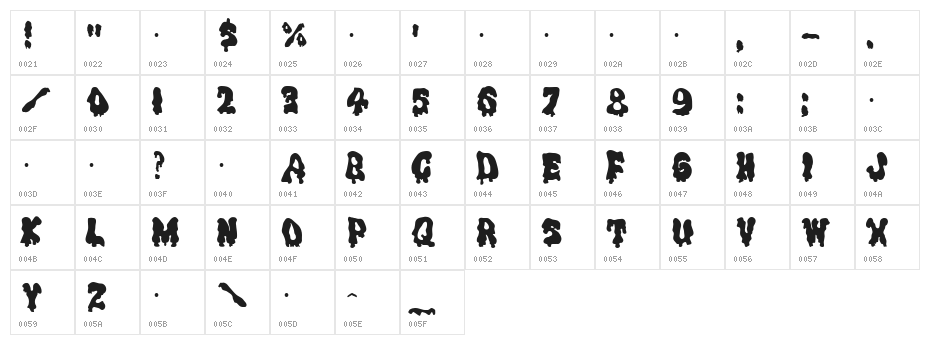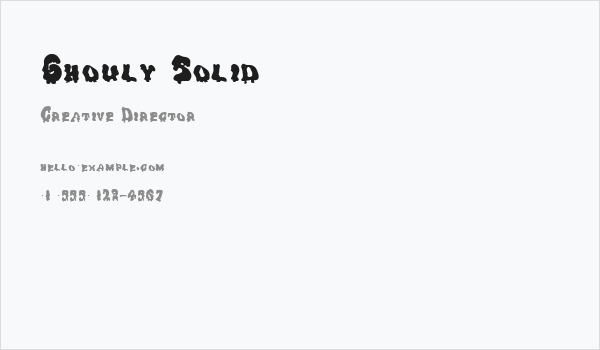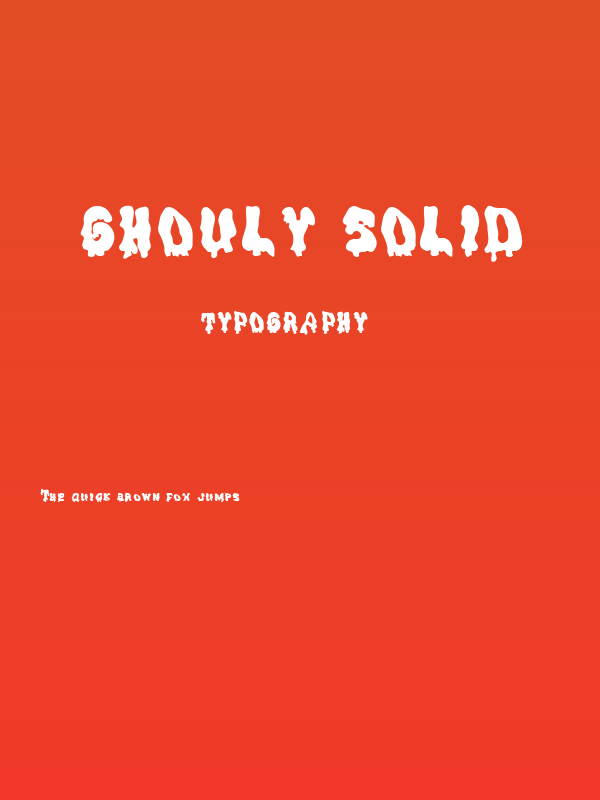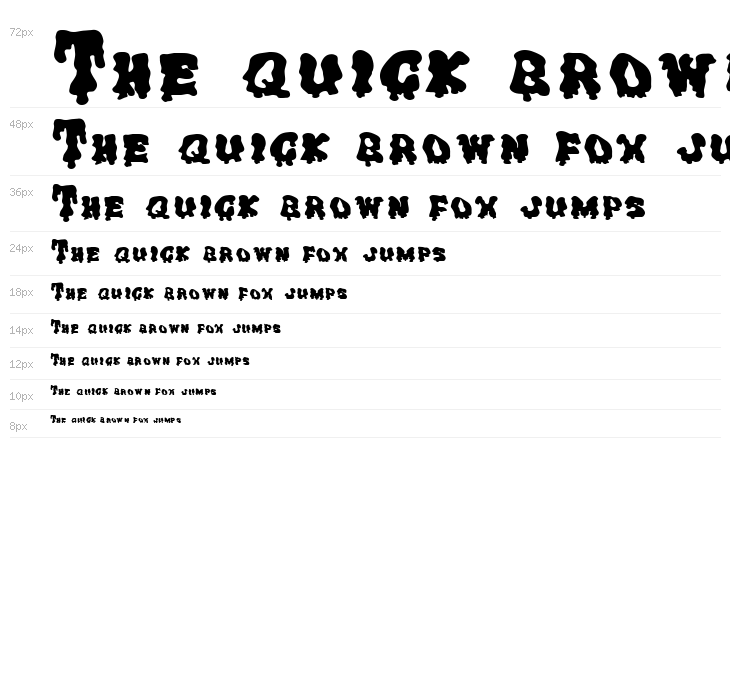
Ghouly Solid Font
| Anwendungsfall | Headlines, Logos, Themed Designs |
| Vorgeschlagene Projekte | Ideal for Halloween invitations, horror movie posters, themed party decorations, or any project needing a spooky, playful touch. |